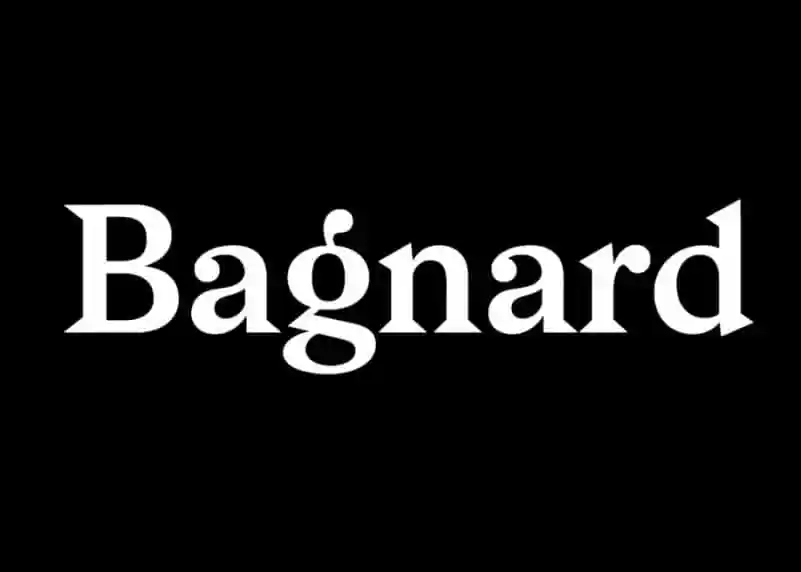
Bagnard Serif é uma elegante e autêntica fonte tipo serif que emociona graças à sua inspiração nos grafites de um preso anônimo dos Napoleões. Inspirada em trabalhos crípticos e criativos da época, essa fonte possui uma simplicidade envolvente que torna a escrita mais chamativa e memorável. Ideal para designers, Bagnard se destaca com suas linhas suaves e detalhes meticulosamente construídos, adequando-se perfeitamente a um vasto range de projetos visuais — desde logotipos até design editorial. Descubra o poder desta fonte em sua próxima criação, ela certamente dará um tom distintivo aos seus trabalhos criativos.